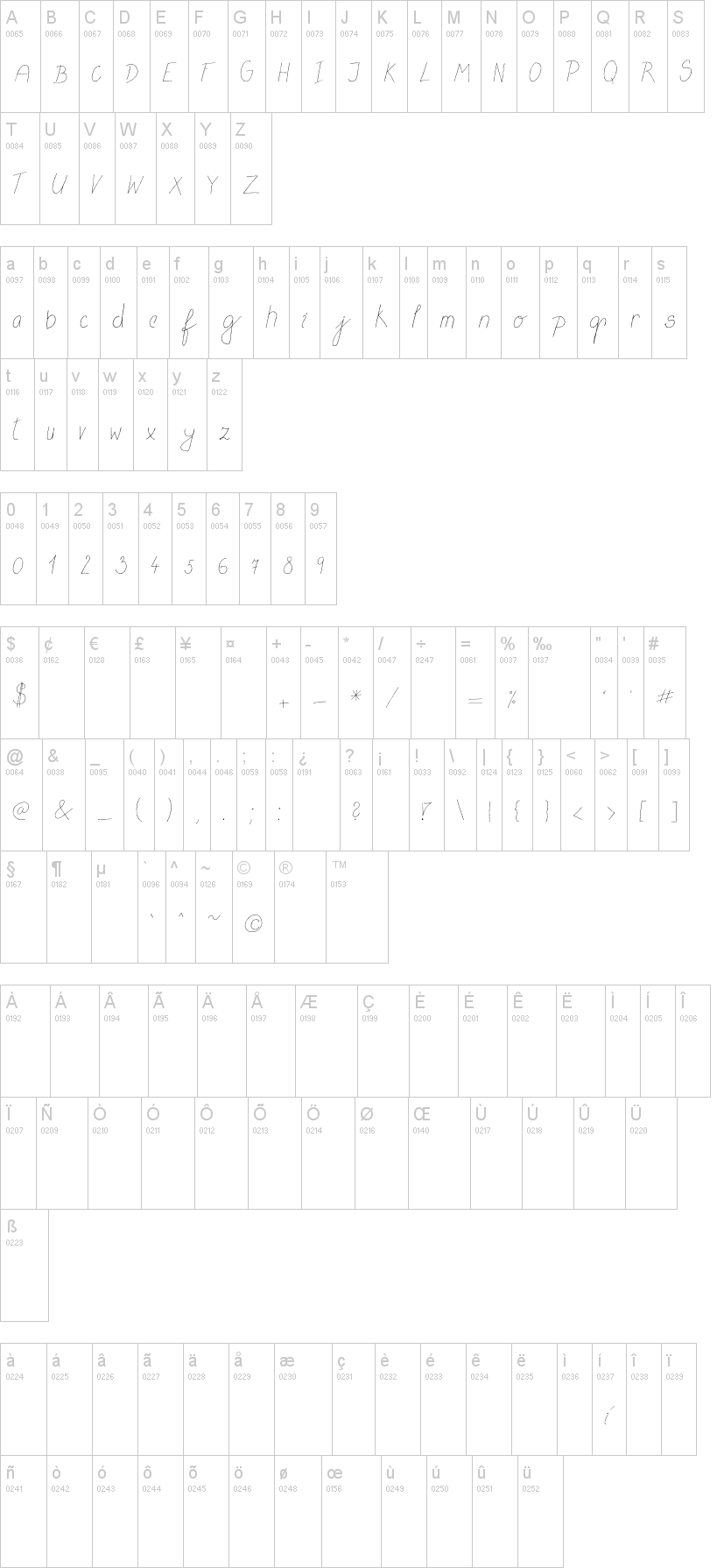
MTF Flowrites
MTF Flowrites 是一款由 Monotype Imaging 公司出品的英文字体,它是一款经典的英文字体,具有流畅的笔画,舒适的曲线和清晰的结构,能够给文字带来极佳的可读性和视觉效果。MTF Flowrites 字体具有优雅的风格,并且具有极佳的可扩展性,可以用于多种印刷和网页应用。MTF Flowrites 字体也可以用于多种语言,例如英语、法语、德语、意大利语等。
MTF Flowrites是一款非常不错的手写艺术字体,具有很好的视觉感,适合于文化类的宣传设计、商业类品牌的广告和产品包装设计以及个性化文字排版等较多场景。
MTF Flowrites字符映射图